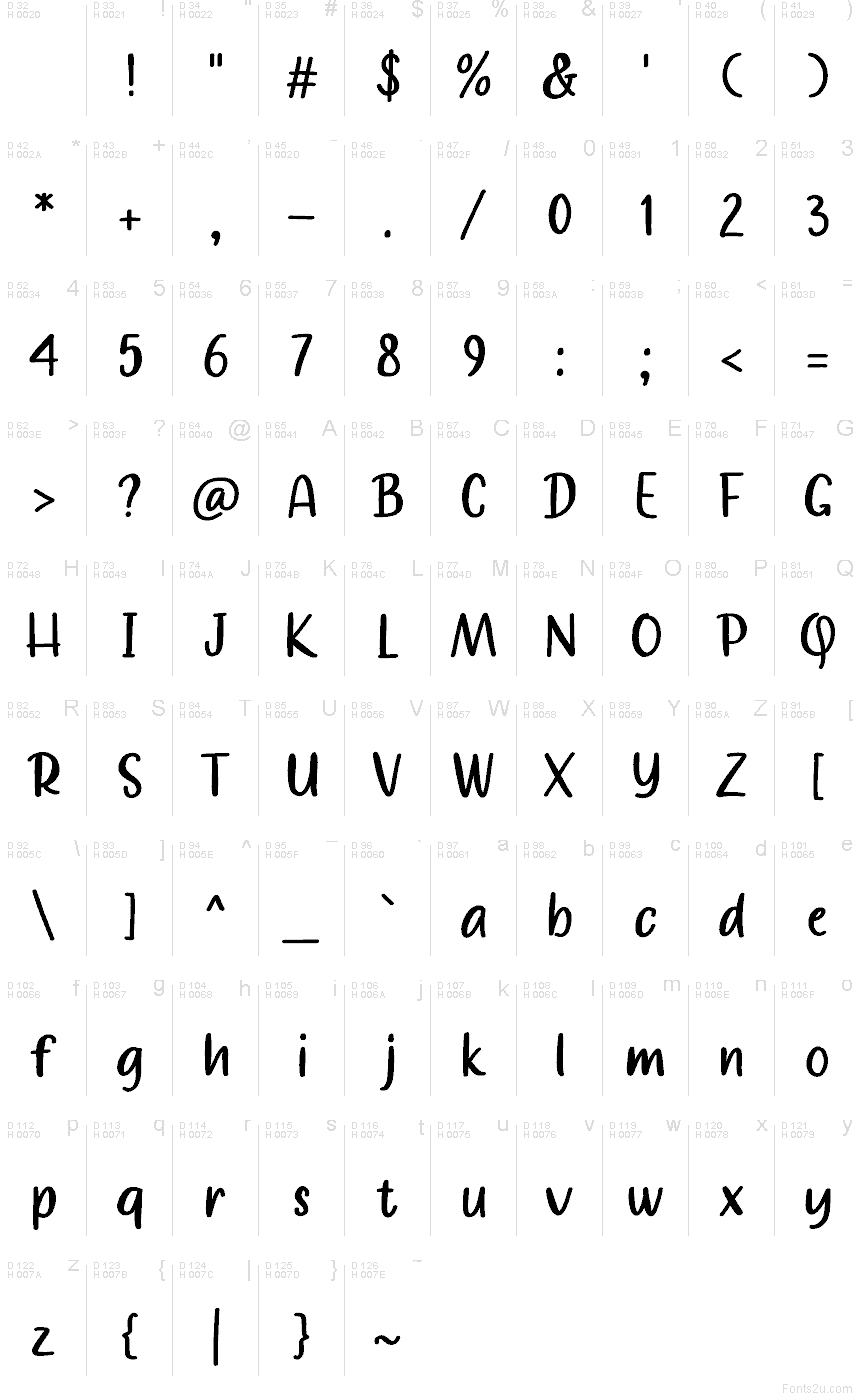
SOUCEK GOAL
Шрифт Soucek Goal від Hello Good Studio — це безкоштовний рукописний шрифт з високими, вузькими літерами. М'які, нерівномірні штрихи надають тексту ритмічності, характерної для письма від руки. Форми залишаються простими та відкритими: поєднання заокруглених ліній з дещо гострішими закінченнями робить накреслення невимушеним, але при цьому структурованим.
Soucek Goal чудово підходить для меню кафе, графіки з цитатами, пакування, постів у соціальних мережах та крафтових етикеток, оскільки його рукописний стиль надає коротким текстам індивідуального, автентичного характеру. Він також добре виглядає в логотипах та акцентних написах на плакатах, коли потрібно досягти розслабленого, але при цьому достатньо чіткого вигляду для назви чи короткої фрази.